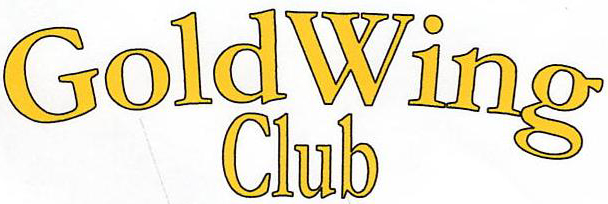
Suche markante Schriftart - ähnlich Bodoni
ich habe schon alles mögliche versucht, die Schrift zu identifizieren - leider bin ich in dem Bereich noch Neuling. Aber bei WTF usw. habe ich es schon versucht. Leider ist dies Problematisch, da die Schrift nur als eingescannte Grafik existiert.
Erstellt wurde es angeblich mal als Wordart - nur welche Schriften installiert waren weiß natürlich keiner mehr nach all den Jahren.
Da die Schrift sehr markant ist, wie ich finde - hoffe ich jemand kann mir helfen.
Sehr auffällig finde ich das große G sowie kleine g und vor allem das große W zudem die spitzen vom d oder i. Da die schrift leicht gebogen wurde kommt einiges wie der strich unten beim kleinen l sicher vom krümmen.
Wenn da mal keine Motorradliebhaber am Werk sind. ;-)
Aber die Schrift ist nicht der Bodoni ähnlich, die geht eher in Richtung Stempel Garamond/Sabon. Das Wort Club wurde dabei übrigens unschön zusammengeschoben.
… es ist eine Garamond Bold, um ganz genau zu sein ;-). Und den "Club" haben die schweren Jungs wohl auf 63 Prozente Breite zusammengestaucht.
… es ist eine Garamond Bold, um ganz genau zu sein ...
Sooo genau ist der Begriff Garamond Bold auch wieder nicht ...  8-)
Es liegt mir natürlich fern hier herum zu stänkern, nur die Aussage Garamond Bold sei ›ganz genau‹ fand ich etwas übertrieben.
Der mittlere Schnitzeljunior sagte, es ist die ...
Er fragte mich, warum da so oft GoldWing steht, ich habe ihm das erklärt und der Rest ging fast alleine ...  :nicken:  :-o
Woher wisst Ihr das ? Oder wie erkennt Ihr die Schriftarten?
Oder wie erkennt Ihr die Schriftarten?
So wie der Metzger die Wurstsorten, der Schreiner die Hölzer, der Steinmetz die Steinarten, der Chirurg die Inneren Organe …
Lach, stimmt! Um es kurz etwas genauer zu umreißen: Schriften kann man in bestimmte Kategorien (»Wurstsorten«, um bei Pachulkes schönem Beispiel zu bleiben) einteilen, die sich jeweils durch spezifische grafische Stilmittel voneinander unterscheiden. Innerhalb dieser Kategorien gibt es dann noch mal Unterkategorien und auch durchaus zeitliche Moden, durch die innerhalb der Kategorien noch einmal präzisiert werden kann. In jeder Kategorie gibt es außerdem besonders beliebte Vertreter, die häufiger verwendet wurden/werden und dadurch auch bekannter sind – und dadurch hier wiederum häufiger gesucht werden. Bei der Identifikation einer unbekannten Schrift gehen wir also nach dem Ausschlussprinzip vor. Oder frei nach Sherlock Holmes: Wenn man alle unmöglichen Optionen ausschließt, muss das, was übrig bleibt, die Lösung sein.  ;-)